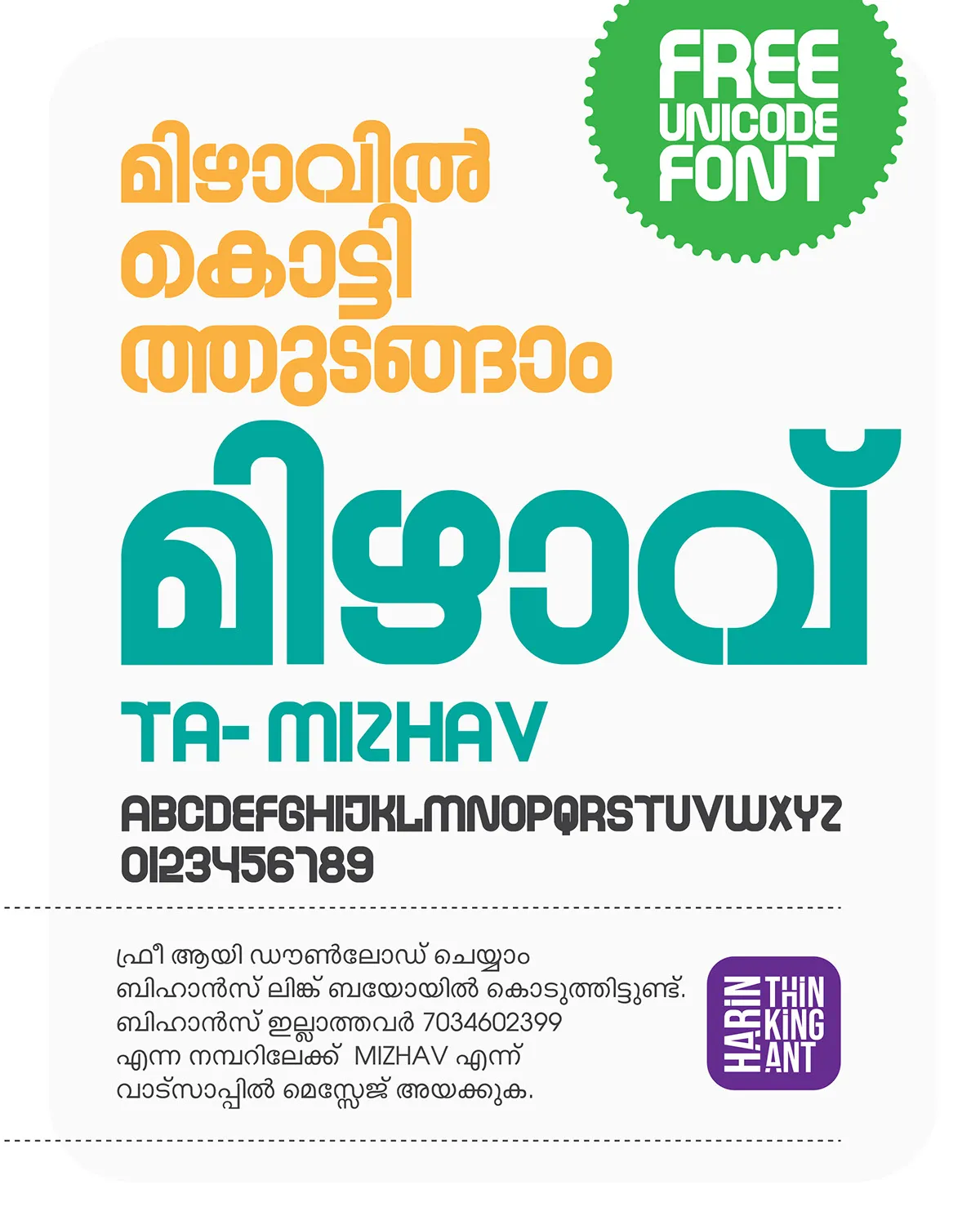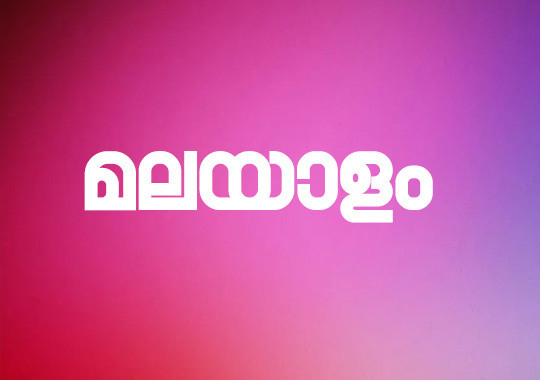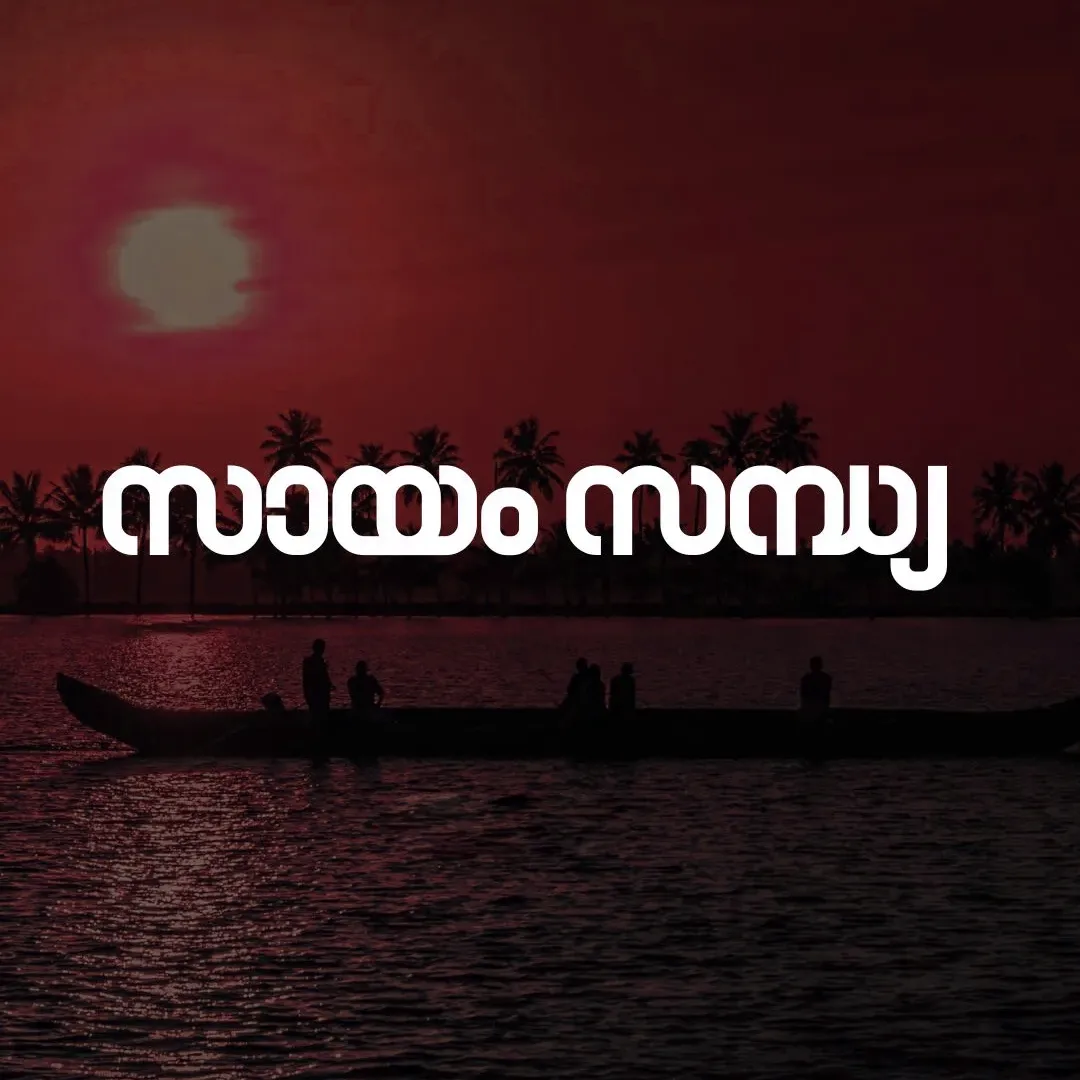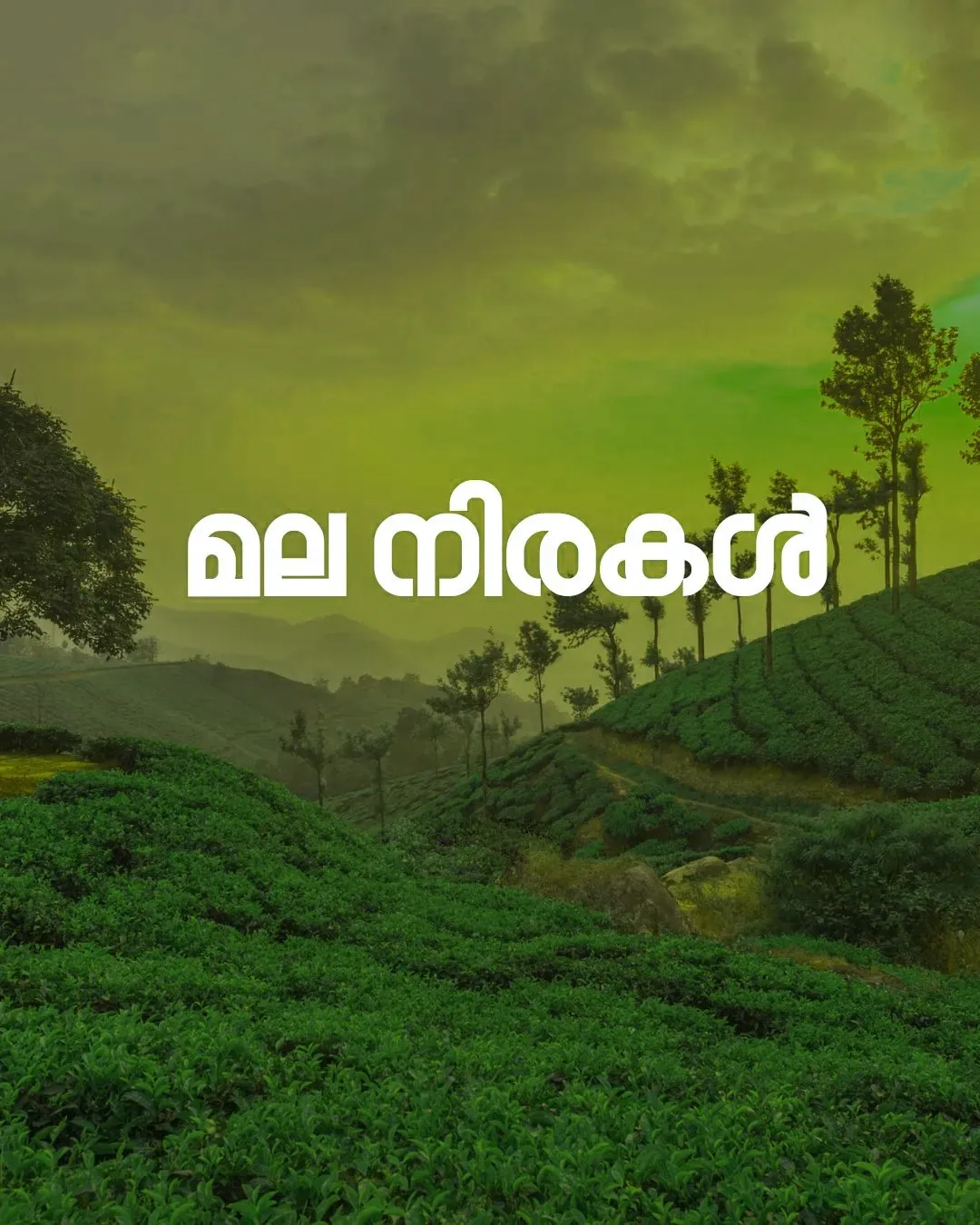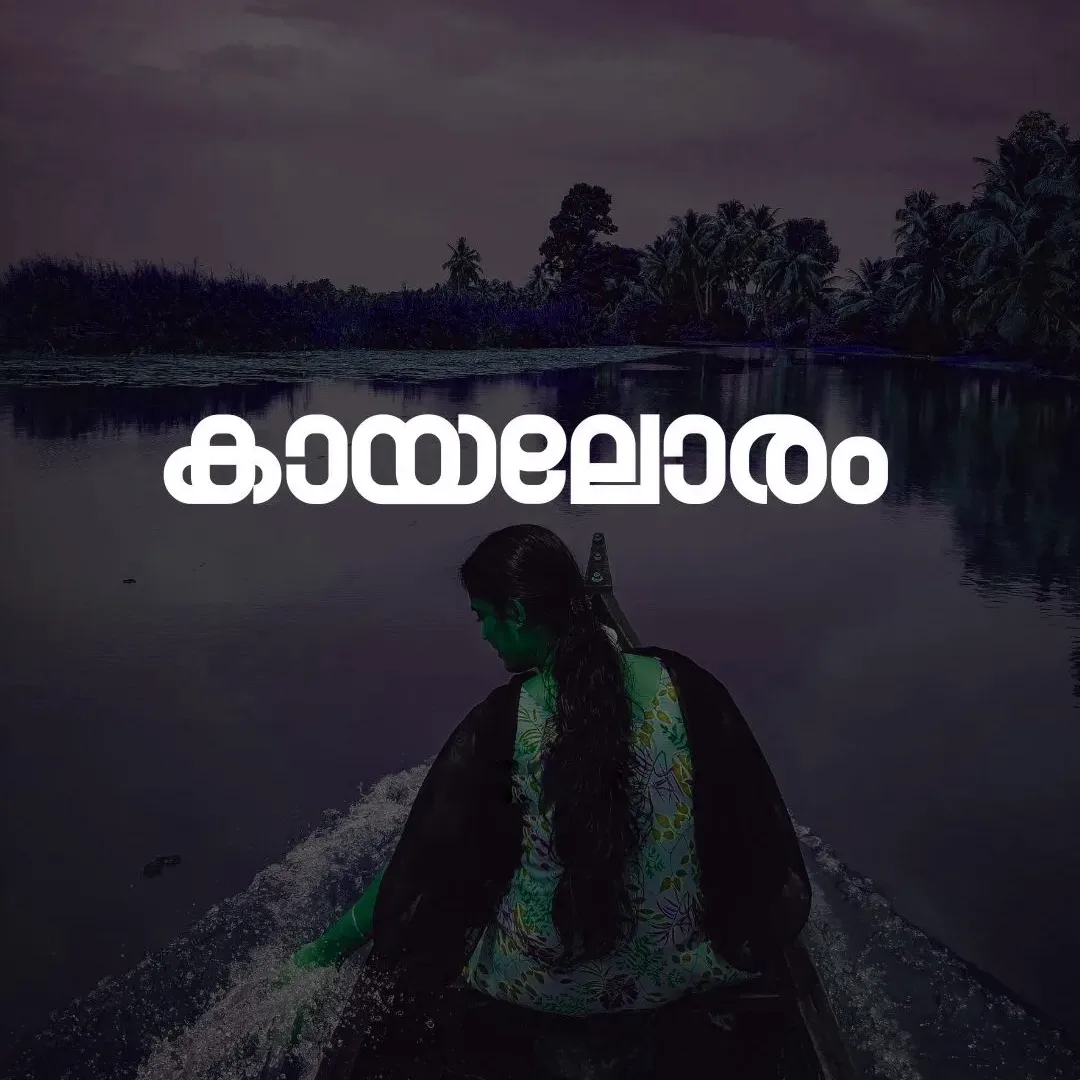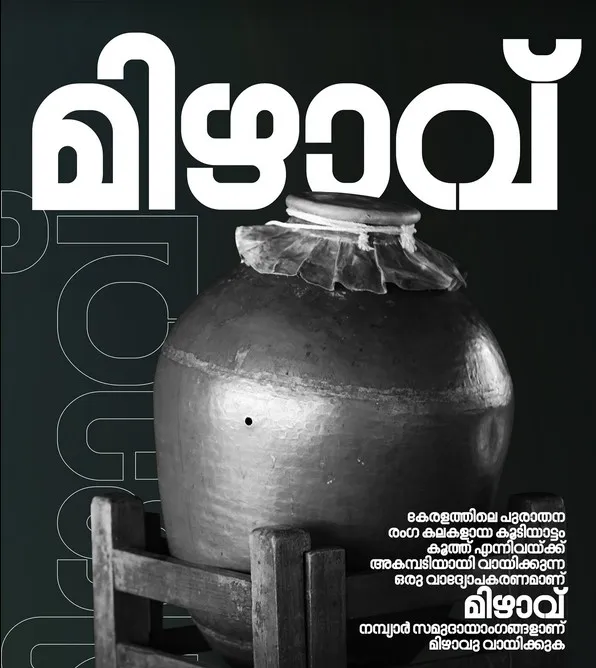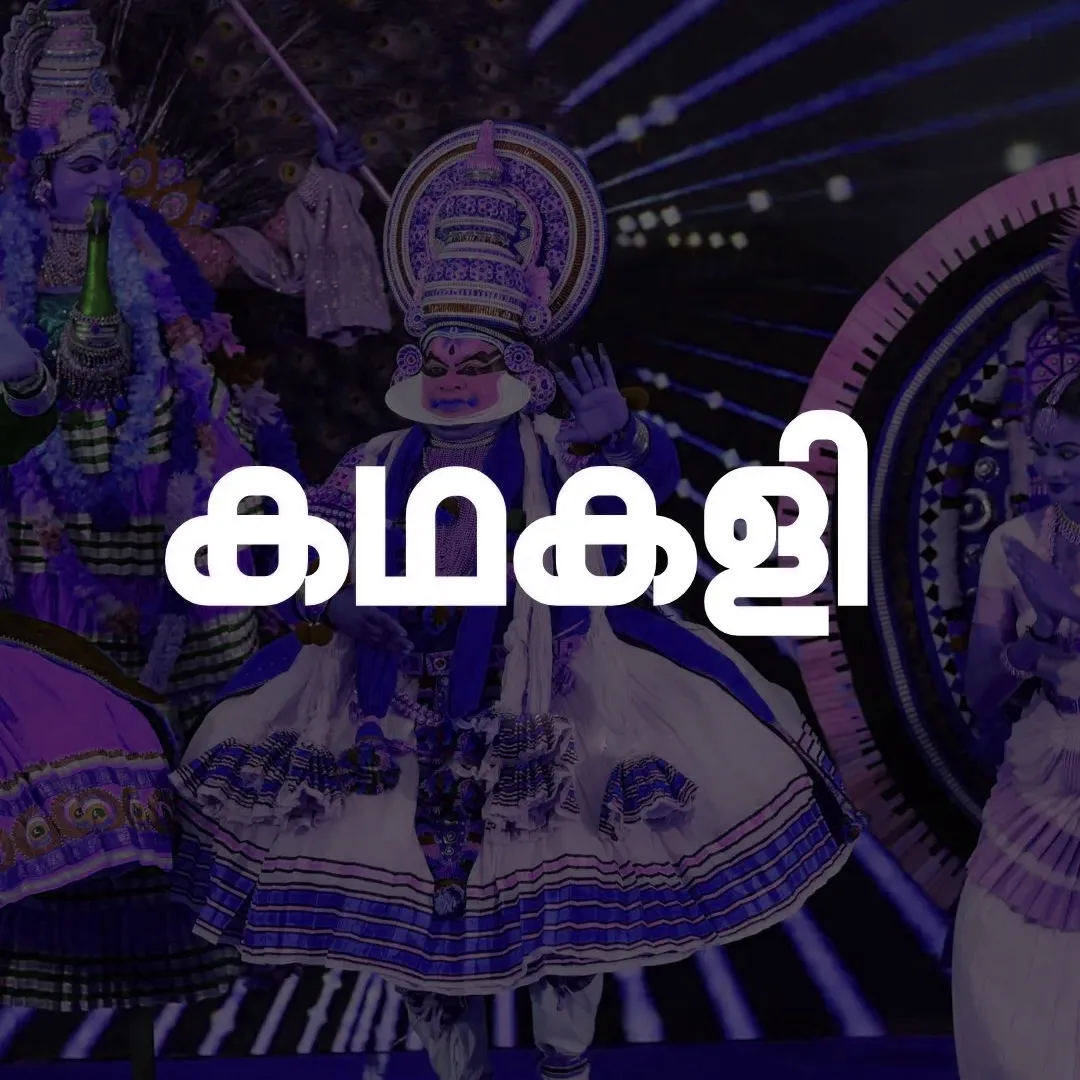
TA-Mizhavu | Stylish Malayalam Unicode Display Font
മലയാളം ഡിസൈൻ ലോകത്തേക്ക് 2025-ൽ പുറത്തിറങ്ങിയ ശ്രദ്ധേയമായ ഒരു യൂണിികോഡ് ഡിസ്പ്ലേ ഫോണ്ടാണ് TA-Mizhavu (മിഴാവ്). പ്രശസ്ത ഡിസൈനറായ ഹരിൻ പുന്നപ്ര (Harin Punnapra) രൂപകല്പന ചെയ്ത ഈ ഫോണ്ട്, തനിമയാർന്ന അക്ഷരരൂപങ്ങളാൽ ഡിസൈനർമാരുടെ പ്രിയപ്പെട്ടതായി മാറിക്കഴിഞ്ഞു. ThinkingAnt Harin ആണ് ഈ ഫോണ്ടിന്റെ പബ്ലിഷർ.
പ്രത്യേകതകൾ:
Modern Display Style: തലക്കെട്ടുകൾക്കും (Headlines) ബ്രാൻഡിംഗിനും (Branding) ഒരുപോലെ ഉപയോഗിക്കാൻ സാധിക്കുന്ന മോഡേൺ ലുക്ക് ഈ ഫോണ്ടിനുണ്ട്.
Versatile Use: ബ്രാൻഡിംഗിന് പുറമെ ബോഡി ടെക്സ്റ്റുകൾക്കും ഡിസ്പ്ലേ ആവശ്യങ്ങൾക്കും ഈ ഫോണ്ട് മികച്ച വായനാസുഖം നൽകുന്നു.
ഡിസൈനുകളിൽ വ്യത്യസ്തമായ ഒരു മലയാളി ടച്ച് കൊണ്ടുവരാൻ ആഗ്രഹിക്കുന്നവർക്ക് മിഴാവ് ഫോണ്ട് വലിയൊരു സഹായമായിരിക്കും.